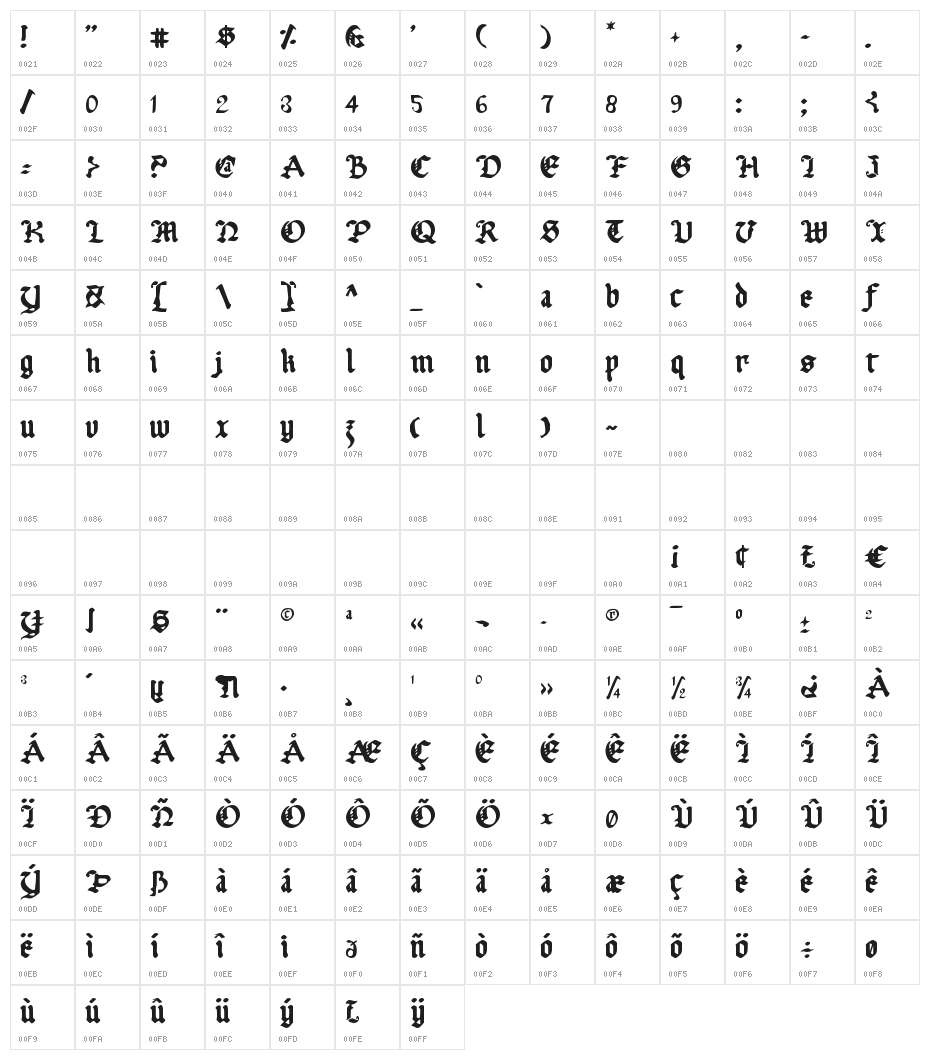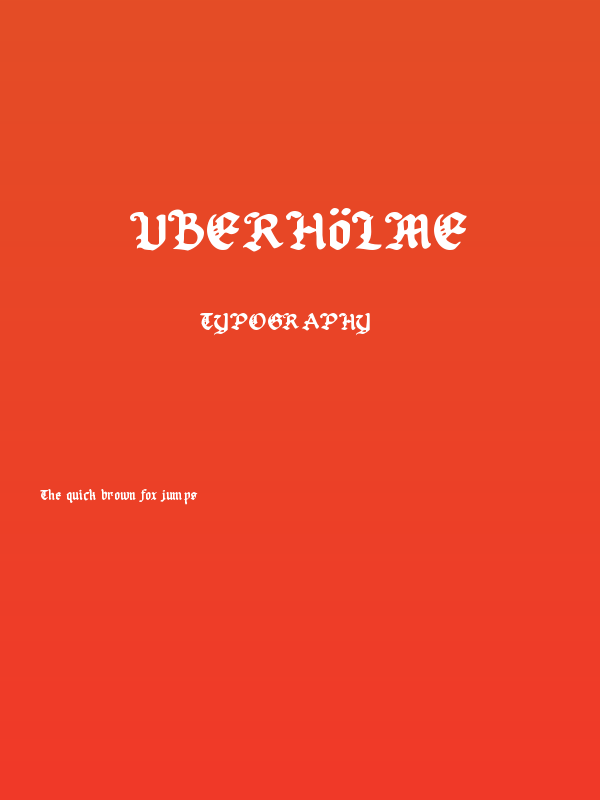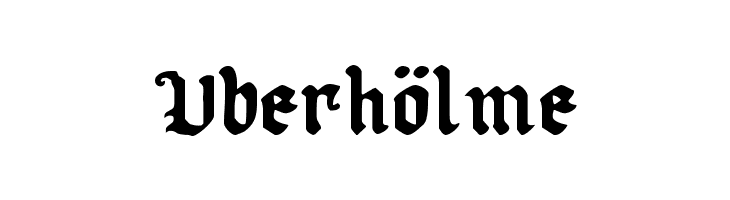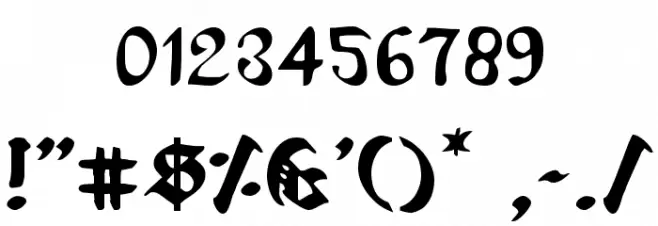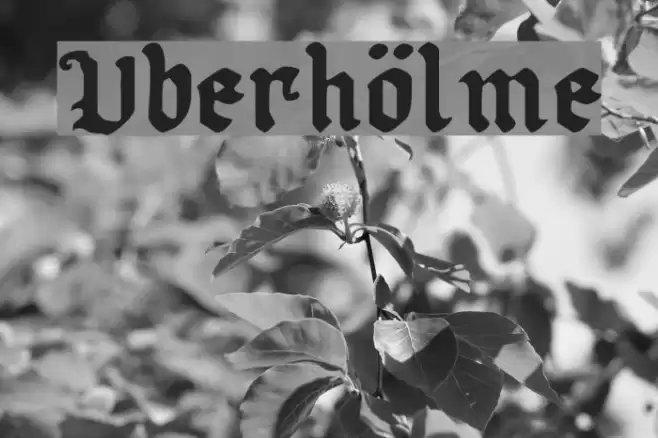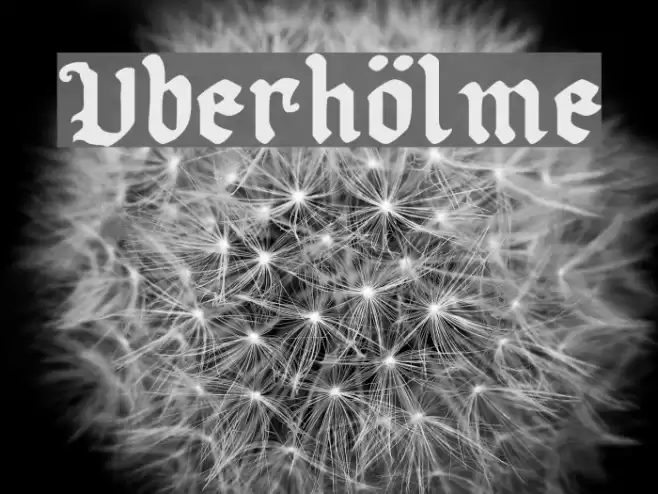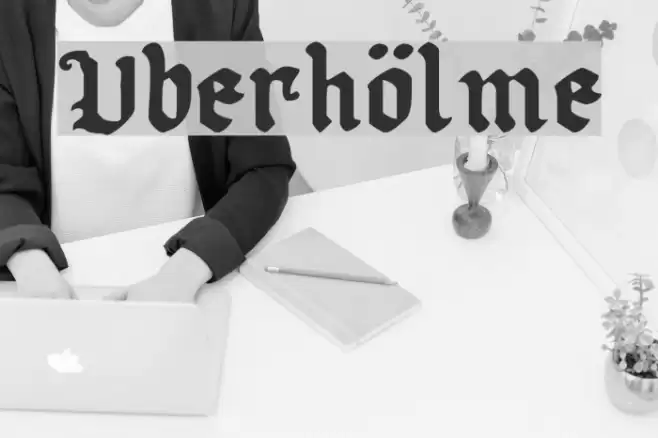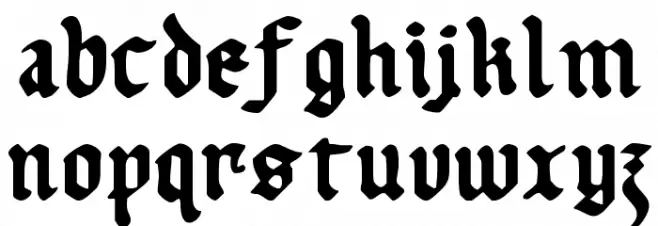
Uberhölme Font
| Estilo general | Vintage |
| Caso de uso | Logos, Headlines, Decorative text |
| Proyectos propuestos | Ideal for projects requiring a vintage or medieval touch, such as historical documents, themed event invitations, or branding for traditional products. |